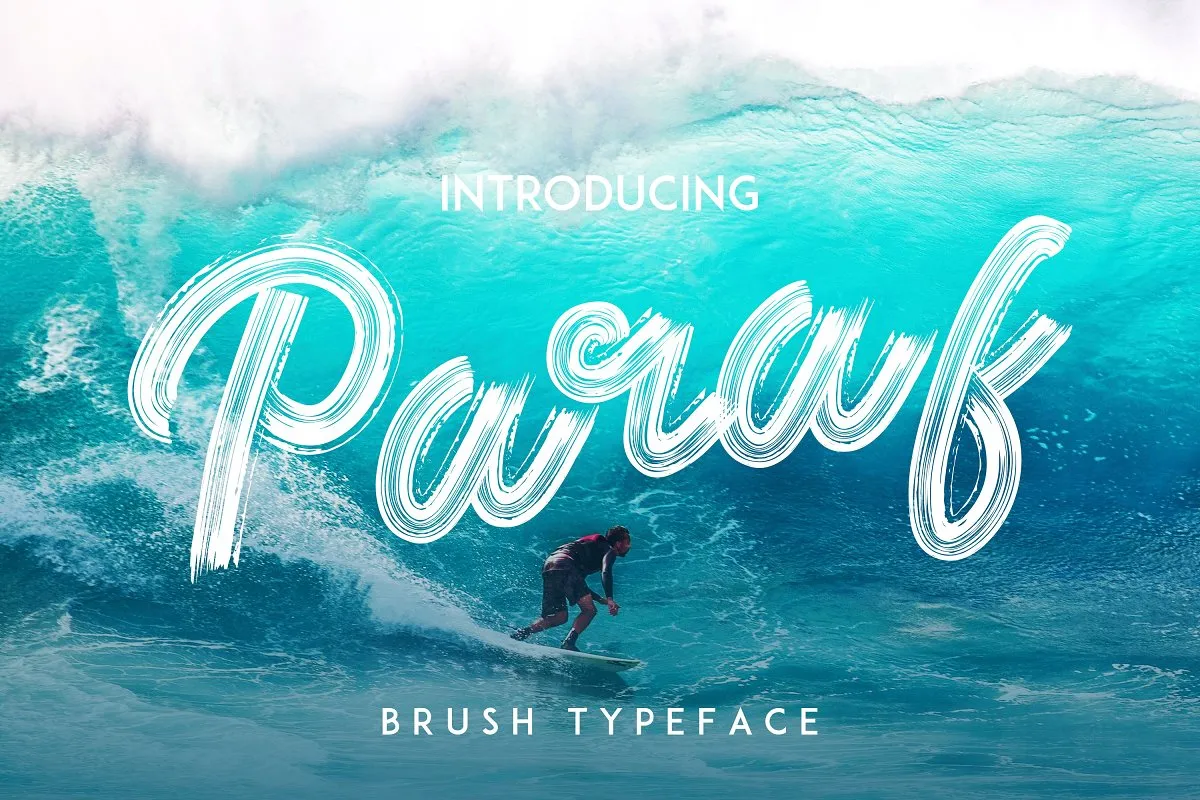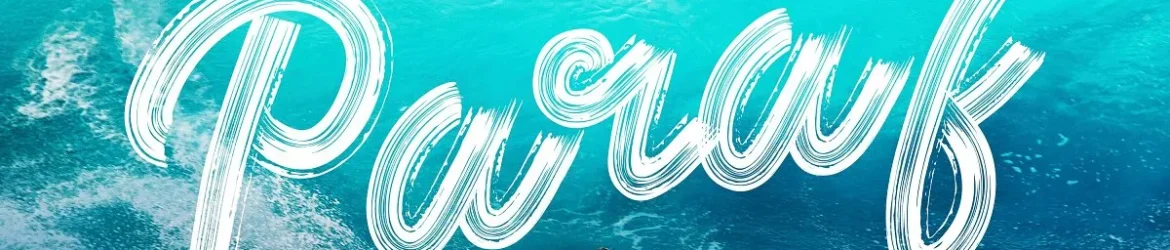
Paraf Brush Font – Download Grátis
Paraf Brush Font é uma fonte script única que traz consigo a textura do pincel, criando um ar rico e autêntico para qualquer design. Suas linhas irregularmente desenhadas garantem que esta fonte seja versátil o suficiente para atender aos mais diversos requisitos de tipo. Ideal tanto para trabalhos como designs em pinturas à mão ou escrita a mão forte, Paraf Brush Font também é perfeitamente adequada para t-shirts, anúncios, cartões de presentes e até mesmo para capas de livros e cartão de visita – uma ampla gama de aplicativos que requerem um tipo impressionante. Sujeitável ao estilo da pintura à mão, Paraf Brush Font é perfeito para qualquer trabalho em desenvolvimento gráfico. Sua textura única irá trazer vida a sua peça, fornecendo uma aparência autêntica e envolvente sem igual aos seus designs. Para quem procura um tipo versátil que pode se adaptar à variedade de ambientes onde o design está em ação, Paraf Brush Font é a escolha perfeita.